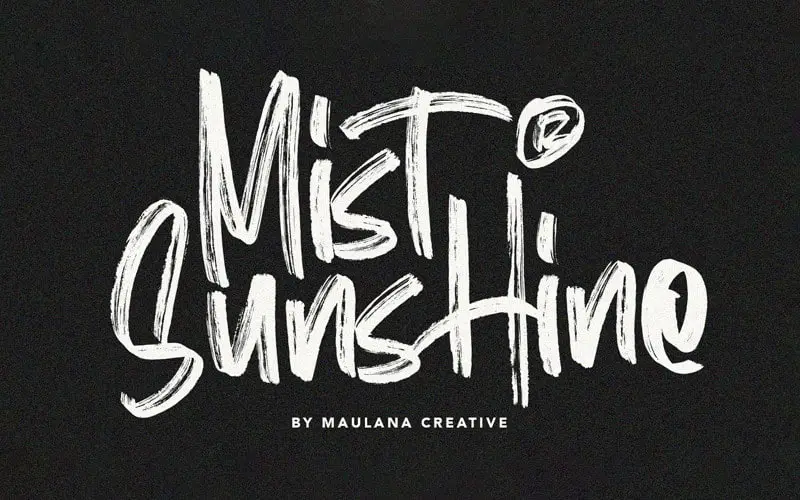
Mist Sunshine Brush Font – Download Grátis
A Mist Sunshine Brush Font é uma fonte de script criada manualmente com a técnica de caneca úmida e esponja de papel. Feita pelo designer Hamilton, essa fonte traz um toque autêntico de uma escrita feita à mão com caneca. Perfeita para o seu próximo design, seja para assinaturas, papéis de carta, logotipos, tipografia de citações, capas de revistas ou livros e cabeçalhos de sites, esta fonte traz um toque único que vai destacar seus trabalhos. Mist Sunshine Font é uma escolha ideal tanto para os profissionais quanto para artistas amadores que buscam criar um design autêntico e único.